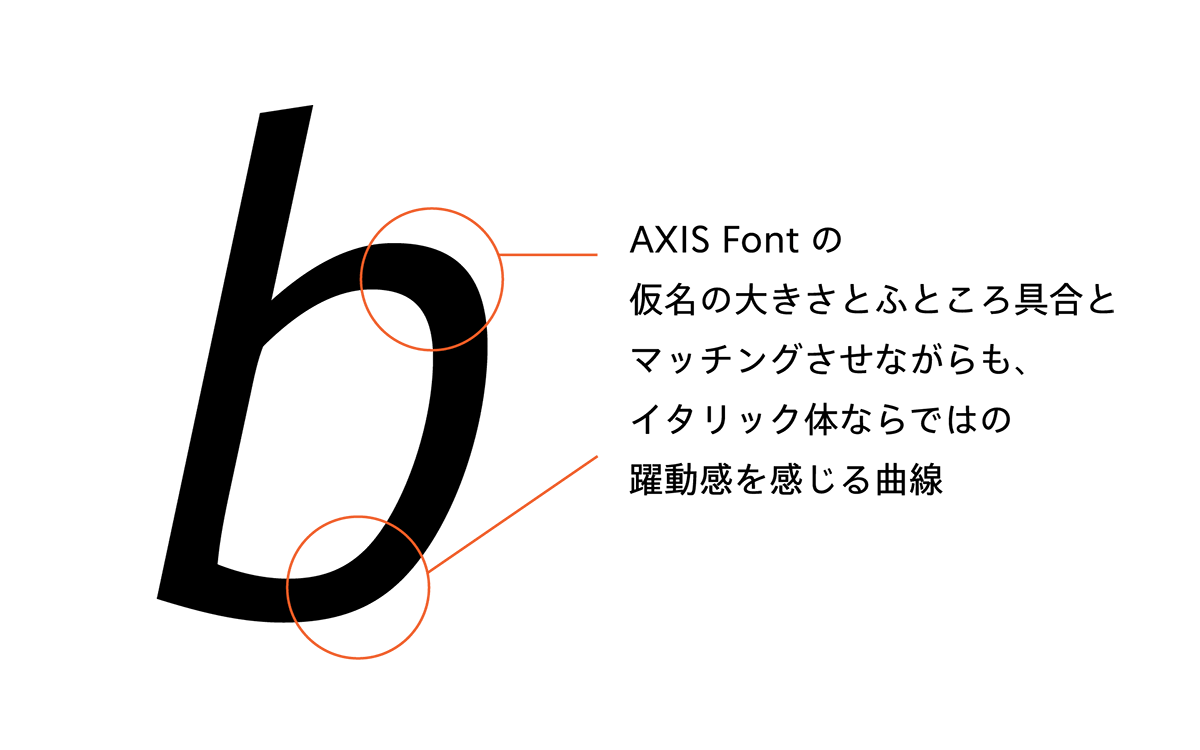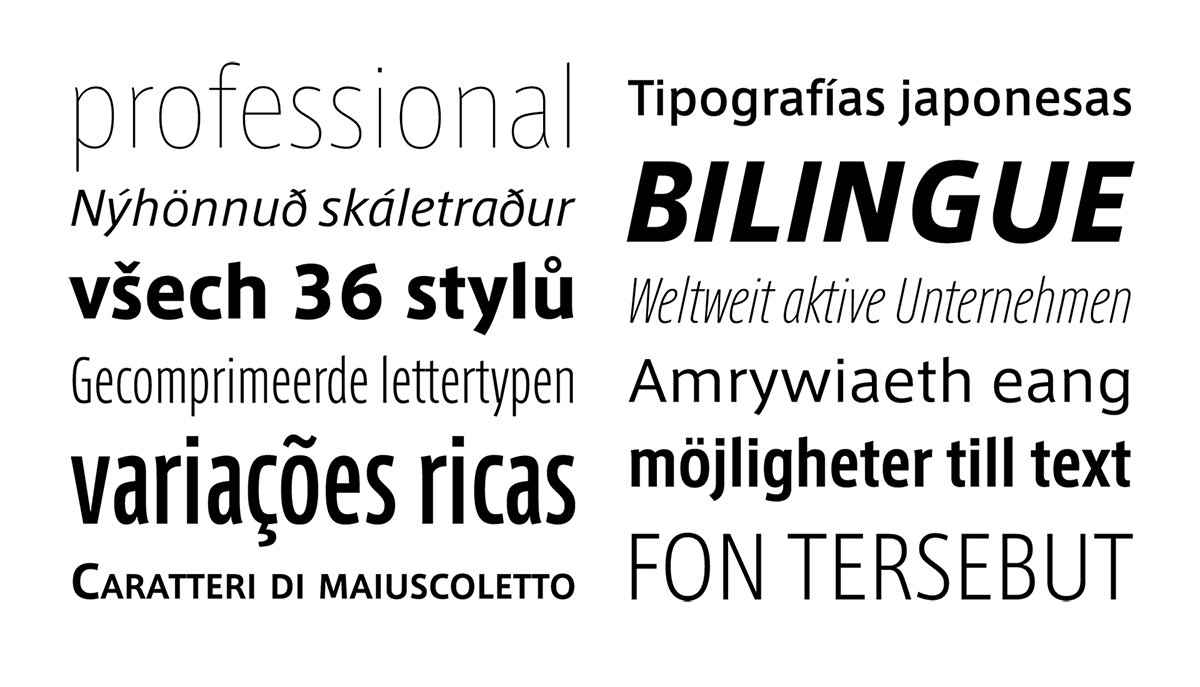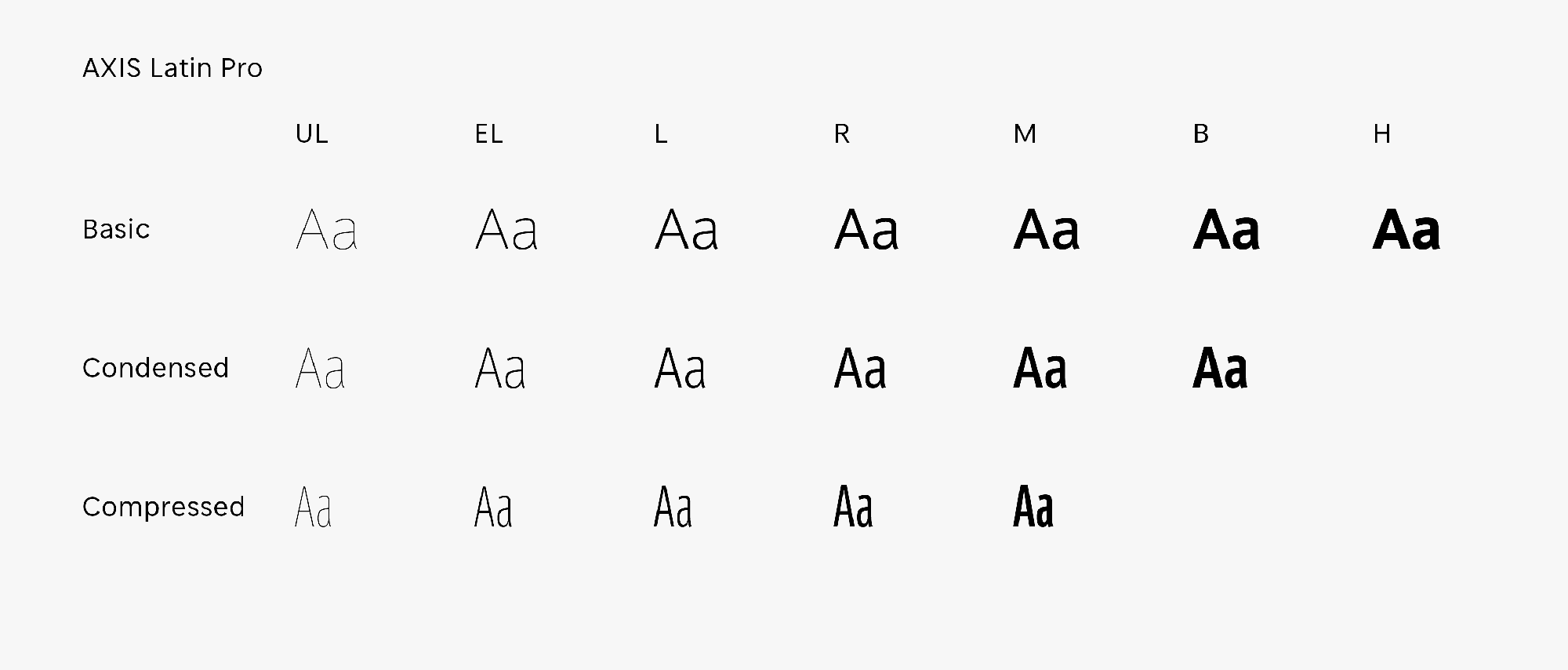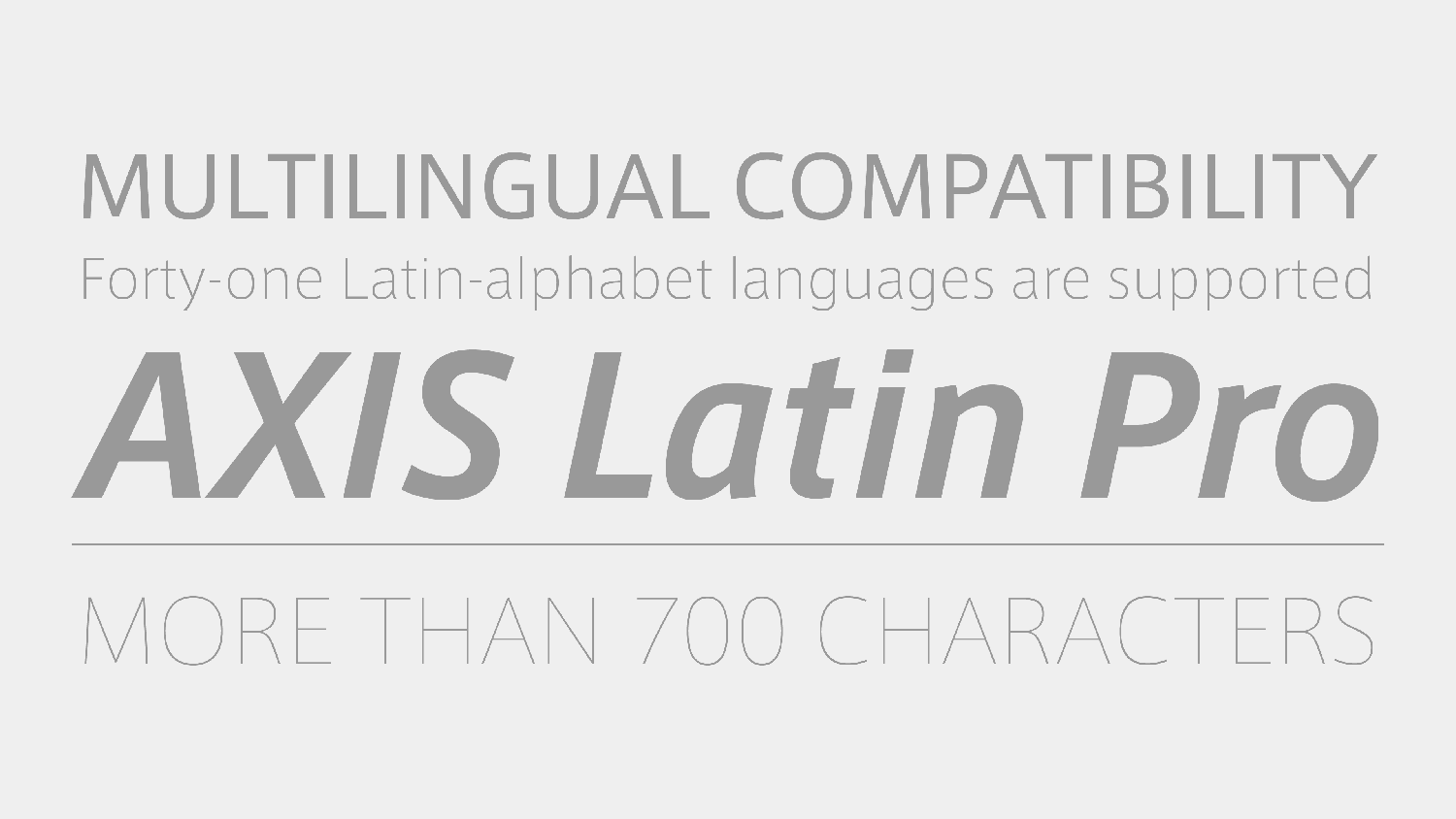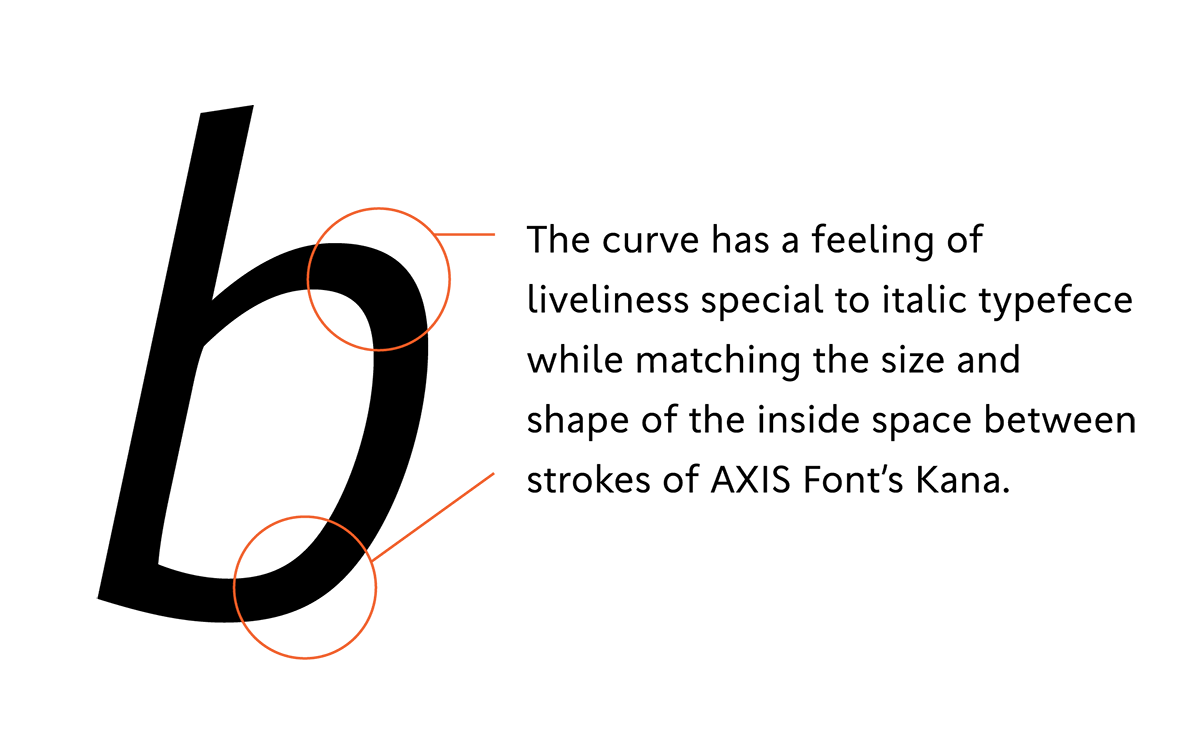
プロ仕様のアルファベット専用書体
AXIS Latin Proは、バイリンガル表記にも対応できる書体として評価の高いAXIS Fontの欧文パートを独立させ、さらなるグローバル化に対応すべくキャラクター数を拡張し56言語に対応しています。また、AXIS Fontの仮名の大きさとふところ具合とマッチングさせながらも、躍動感を感じる曲線のイタリック体やスモールキャップス等追加したプロ仕様のアルファベット専用書体です。正体、コンデンス、コンプレスの多彩なバリエーション展開はそのままに、全36種類にわたるファミリー構成により、幅広い文字表現を可能にする、日本発の欧文フォントです。
56言語に対応したプロ仕様
AXIS Latin Proは下記の56言語に対応しています。
英語、アイスランド語、アイルランド語、アフリカーンス語、アルバニア語、イタリア語、インドネシア語、ウェールズ語、エストニア語、エスペラント語、オック語、オランダ語、オロモ語、カーボベルデ・クレオール語、ガリシア語、カタロニア語、グリーンランド語、クロアチア語(ラテン文字表記)、コーンウォール語、サンゴ語、スイスドイツ語、スウェーデン語、スコットランド・ゲール語、スペイン語、スロバキア語、スロベニア語、スワヒリ語、ソマリ語、チェコ語、ツワナ語、デンマーク語、ドイツ語、ノルウェー語ブークモールおよびニーノシュク、バスク語、ハワイ語、ハンガリー語(Dzは分割表記)、フィリピノ語、フィンランド語、フェロー語、ブラジル・ポルトガル語、フランス語、ブルトン語、ポルトガル語、ポーランド語、マルタ語、マレー語、マン島語、モーリシャス・クレオール語、ラテン語、ラトビア語、リトアニア語、ルーマニア語、ルクセンブルク語、レト・ロマンス語、ロマンシュ語、ワロン語